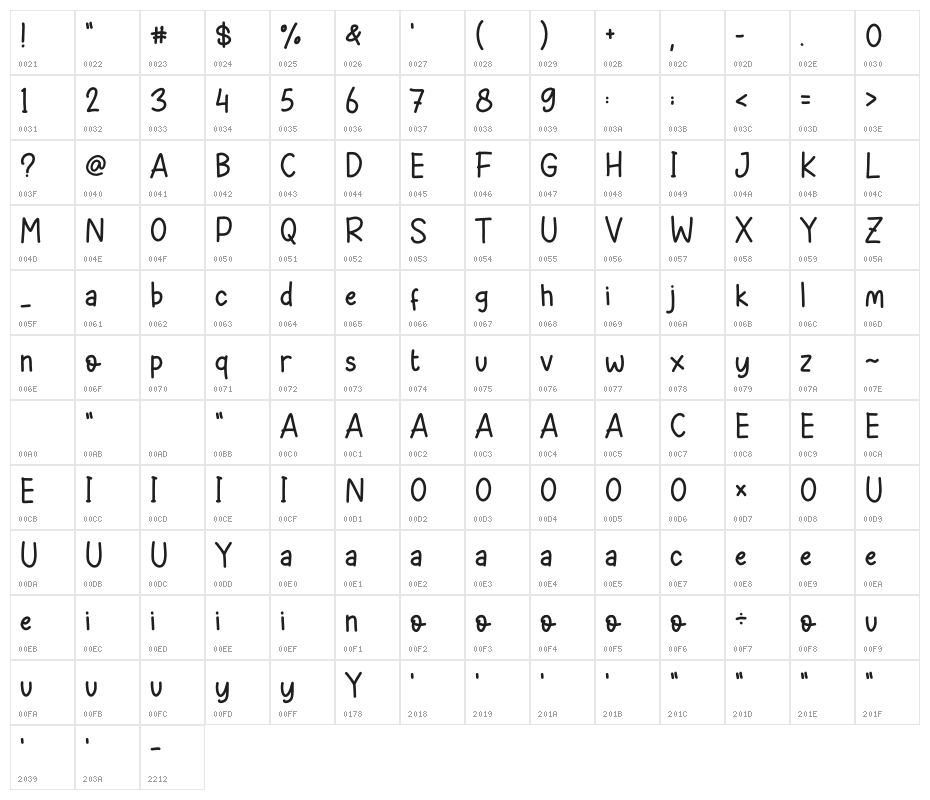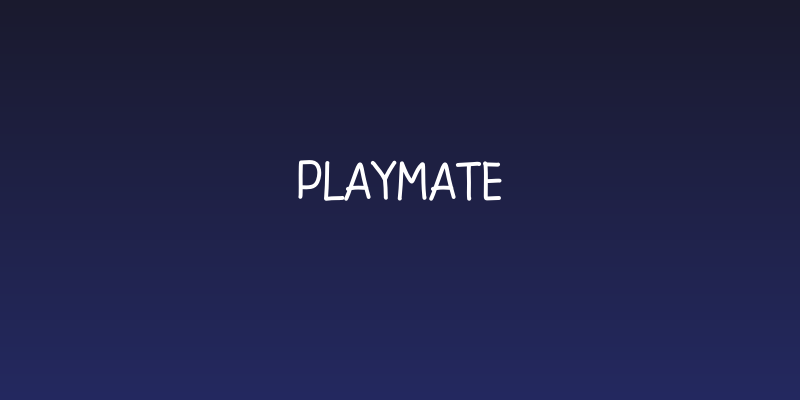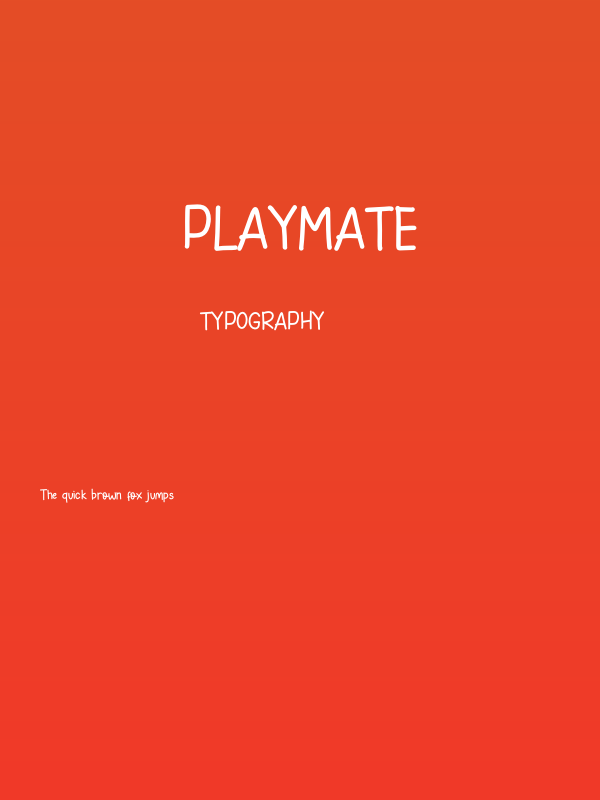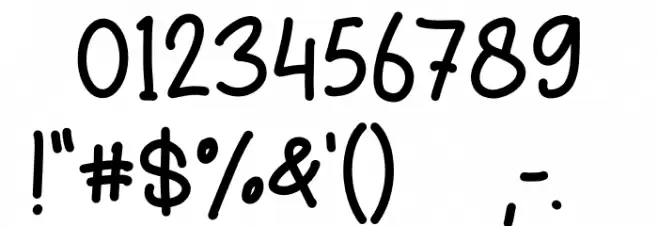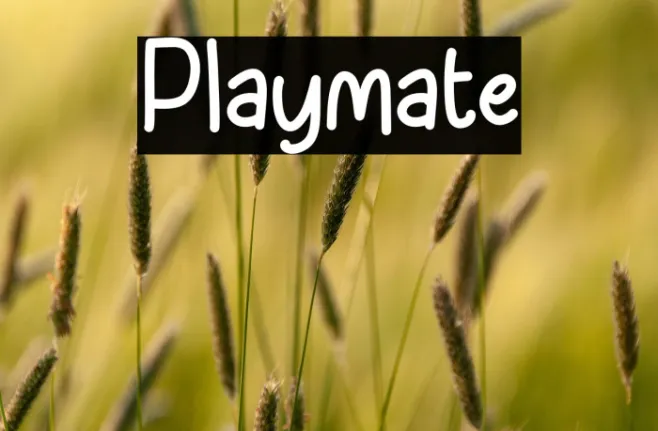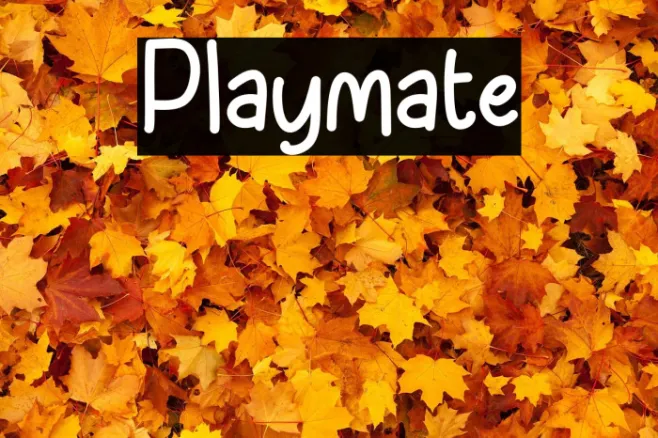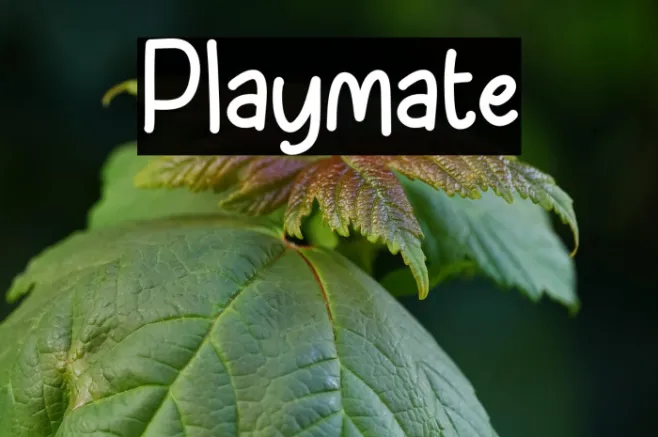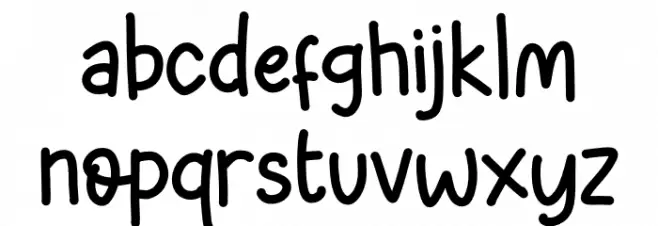
Playmate Font
| Stile generale | Casual, Playful |
| Caso d'uso | Headlines, Informal text, Creative projects |
| Progetti proposti | Ideal for children's books, greeting cards, playful branding, and informal invitations. |